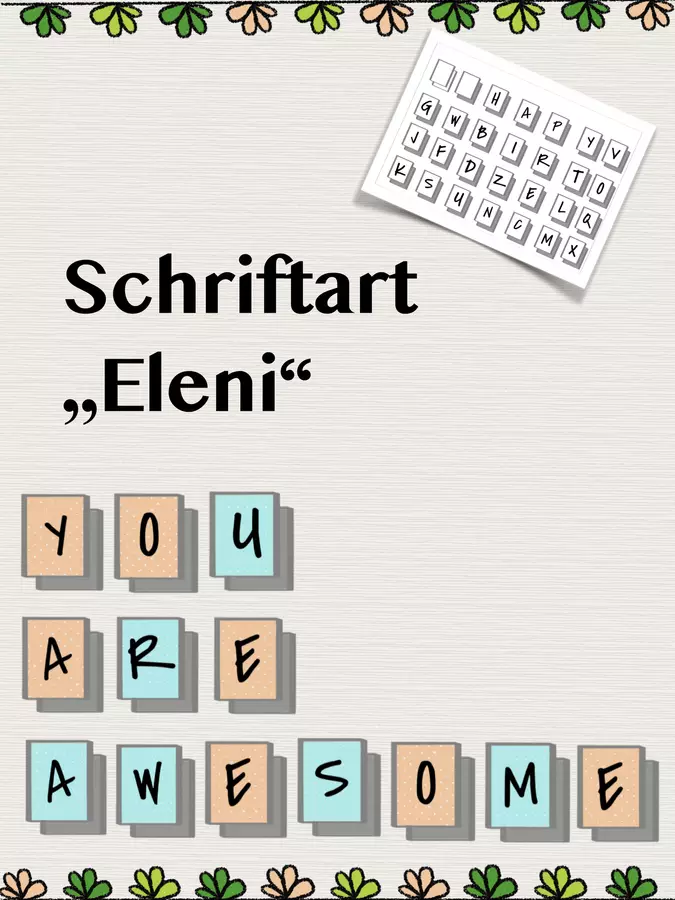
selbst erstellte Schriftarten - Schriftart Font „Eleni“ // Erstellung von Arbeitsblättern PNG Bilddateien - heyhanni - Deckblatt
Hier erhältst du die Schriftart „Eleni“ für die Erstellung von Arbeitsblättern (z.B. Überschriften). Die einzelnen Buchstaben können bis DiNA5 vergrößert werden und du bekommst diese als PNG Bilddateien.
Schriftart Font „Eleni“ // Erstellung von Arbeitsblättern PNG Bilddateien